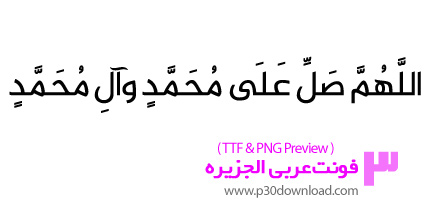
دانلود فونت عربی و فارسی شبکه ماهواره ای الجزیره Al-Jazeera Arabic Typeface
شما کاربران گرامی شاهد فونت عربی و فارسی شبکه ماهواره ای الجزیره با فرمت TTF هستید که میتوانید آن ها را درطراحی های گرافیکی خود به کار ببرید. طراحان و گرافیست های خلاق می توانند از این فونت زیبا در طراحی های خود استفاده کنند.
این فونت، فونت زیبایی است و برای استفاده در قالب سایت و صفحات نمایش می تواند بسیار مناسب باشد. تمام حروف فارسی به این فونت که در سه وزن نازک، معمولی و ضخیم منتشر گردیده اضافه شده و برخی از اشکالات را رفع گشته است.